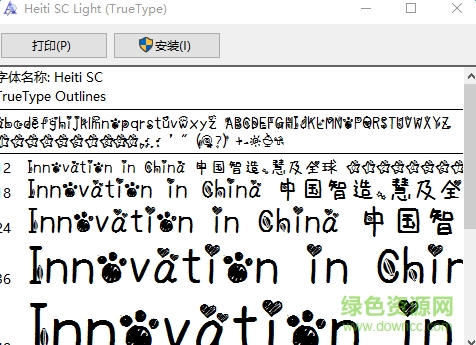
星星銅鑼燒體
星星銅鑼燒體是一款很有個(gè)性的電腦藝術(shù)字體,這款字體最大的特別之處就在于她寫出來(lái)的字上面會(huì)有星星的裝飾品,這樣會(huì)顯得很有個(gè)性、很好看,喜歡這款字體的朋友可以來(lái)綠色資源網(wǎng)下載。
星星銅鑼燒體確實(shí)是一款很不錯(cuò)的電腦字體,不僅字形優(yōu)美,實(shí)用性也很強(qiáng),可以用于很多方面,歡迎大家來(lái)綠色資源網(wǎng)下載。